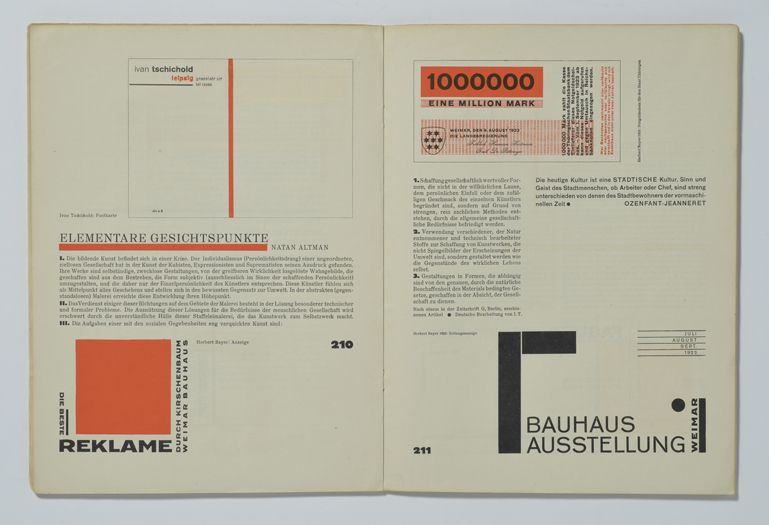
Книга Яна Чихольда «Новая типографика. Руководство для современного дизайнера»
«Новая типографика» Яна Чихольда впервые была опубликована в 1928 году в Германии и стала своего рода манифестом современной типографики. Это доскональное и увлекательное исследование охватывает широкий круг вопросов — от теорий социального критицизма и истории искусств до возрастающей важности фотографии в графическом дизайне. Книга в суперобложке В полном объеме книга на русском языке издается впервые (несколько глав были напечатаны в советском журнале «Полиграфическое производство» в 1929 году). Предисловие к русскому изданию написал Владимир Кричевский. Несмотря на то что описанные в книге стандарты устарели и не используются, а сам Чихольд со временем отказался от многих высказанных идей, «Новая типографика» до сих пор остается одной из важнейших книг XX века, посвященных типографике и графическому дизайну. Издание будет полезно графическим дизайнерам, шрифтовикам, иллюстраторам и верстальщикам, а также широкому кругу читателей, интересующихся историей графического и шрифтового дизайна.
Титульный лист
Книга набрана и сверстана в духе оригинального немецкого издания 1928 года.
Очень полезный, интересный и эмоциональный текст, искрящий идеями. По стилю напоминает манифесты и статьи Казимира Малевича. Сильно заряжены были 1920-е.
Главная мысль книги — нужно жить в ногу со временем и перестать использовать инструменты и принципы работы, которые разрабатывались при совсем других условиях для совсем других целей.
Стр. 14. Инженер — творец нашего времени. Признаки его произведений: экономичность, точность, проектирование на основе четких форм, соответствующих функции предмета.
25. Германию, победившую во Франко-прусской войне, наводнили штампованные копии вещей, которые раньше делались вручную. Такое барахло с восторгом раскупалось, потому что оно символизировало победоносное окончание войны. Более того, этой дрянью даже гордились. Как и современные нувориши, в то время люди прельщались фальшивым блеском любой подделки. Полностью отсутствовало ощущение подлинности.
32. Попыткам создания единой формы из чересчур оригинальных шрифтов мы сегодня противопоставляем осмысленную, неиндивидуальную работу с безличными структурными формами. Это единственная возможность совместного свободного творчества, осмысленная реализация подлинных индивидуальных талантов для создания целостностных форм (стиля). Индивидуальные особенности и «почерк художника» противоположны нашим стремлениям.
Только анонимные структурные формы, использование общих абстрактных законов и отказ от личного тщеславия (до сих пор его ошибочно называли индивидуальностью) в пользу чистого формообразования создадут единую культуру, которая проникнет во все сферы жизни ( в том числе и в типографику).
55. Примечательно, что Петер Беренс в некоторых из оформленных им книг использовал гротеск в качестве основного шрифта. И в Голландии представители стиля модерн, с которым прямо и непосредственнр связаны Ауд, Мондриан и Дусбург, с самого начала в качестве основного шрифта использовали гротеск (правда, по началу искаженный). В обоих случаях к этому шрифту пришли потому, что искали простейшую, первоначальную шрифтовую форму. Сторонники констуктивного направления стиля модерн предпочитали именно такую форму.
64. В одном из номеров журнала «Мерц» Эль Лисицкий опубликовал нижеследующие тезисы:
Топография типографики
- Слова, напечатанные на листе, воспринимаются глазами, а не на слух.
- С помощью обычных слов представляются понятия, а с помощью букв понятия могут быть выражены.
- Экономия восприятия — оптика вместо фонетики,
- Оформление книжного организма с помощью наборного материала по законам типографской механики должно соответствовать силам сжатия и растяжения текста.
- Оформление книжного организма с помощью клише реализует новую оптику. Сверхъестественная реальность совершенствует зрение.
- Непрерывная последовательность страниц — биоскопическая книга.
- Новая книга требует новых писателей. Чернильница и гусиные перья мертвы.
- Напечатанный лист побеждает пространство и время. Напечатанный лист и бесконечность книги сами должны быть преодолены.
В 1923 году на выставке Баухауса он познакомился с движением модернистов и примкнул к нему, отвергнув привычные шрифты и симметричную композицию в пользу шрифтов без засечек, простых геометрических конструкций и асимметрии. Его работы демонстрировали свойственный тому периоду рационализм, были практичны, эстетичны и созданы с учетом новых технологий печати.